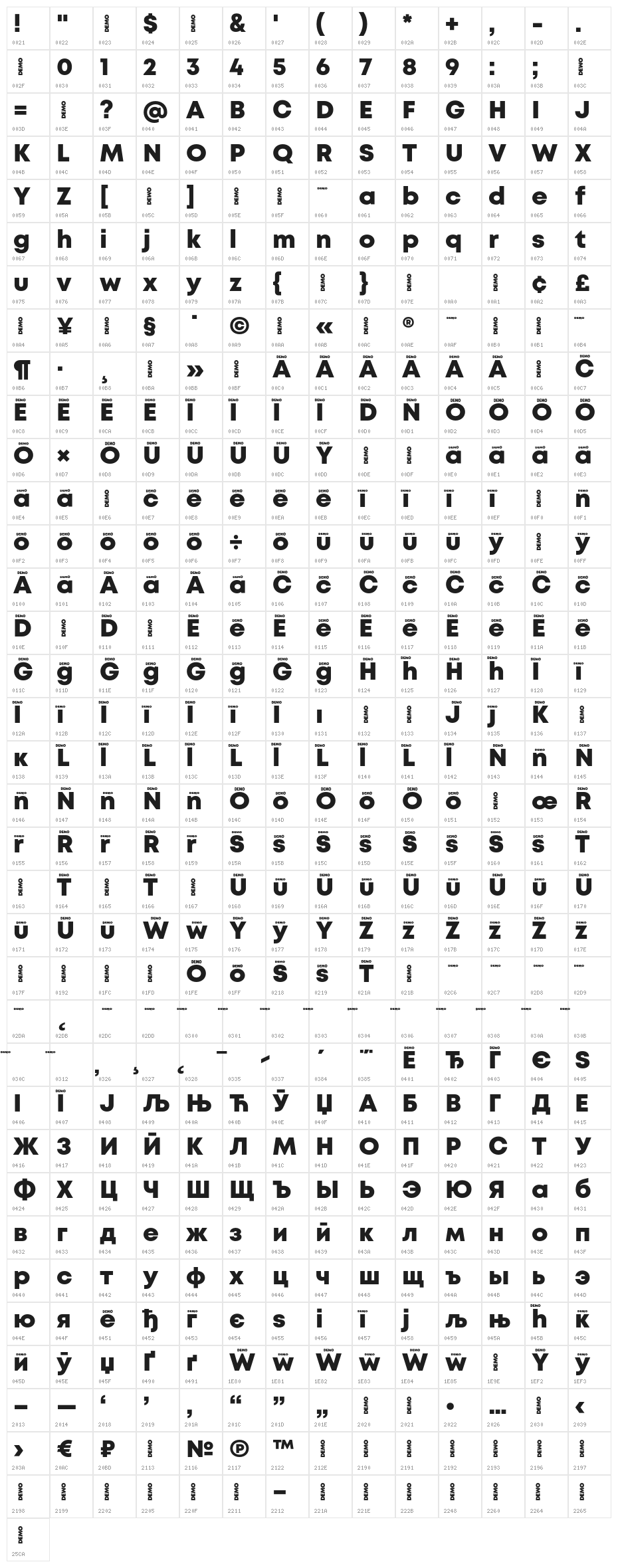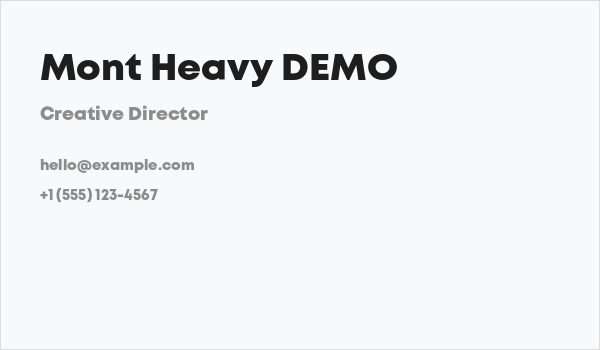
Mont Heavy DEMO Font
✎ Sans Serif
| Proyectos propuestos | Ideal for branding, headlines, posters, and digital media where a strong visual impact is needed. |